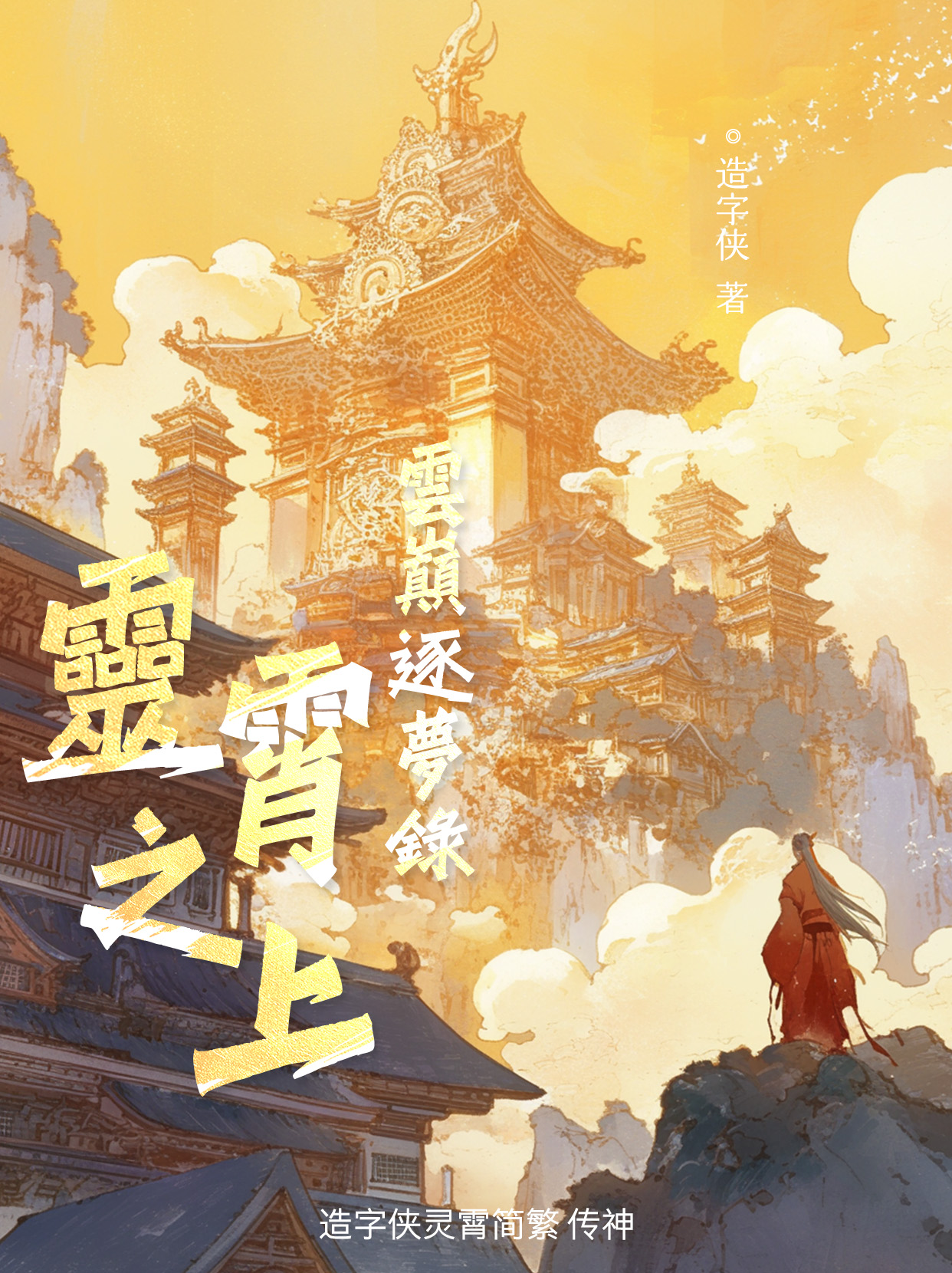
造字侠灵霄简繁 传神
PlayFont-LingxiaoGBT
造字侠灵霄简繁 传神
手写体
大黑(Bold)
灵霄宝殿九重天
造字侠灵霄简繁传神 是一款硬笔手写字,名字来源于《西游记》玉皇大帝的居所灵霄宝殿。字体笔画硬挺利落,字形古风劲萧,饱满均匀,结构布局沉稳,笔力劲健,适用于仙侠、网游等海报标题用字。